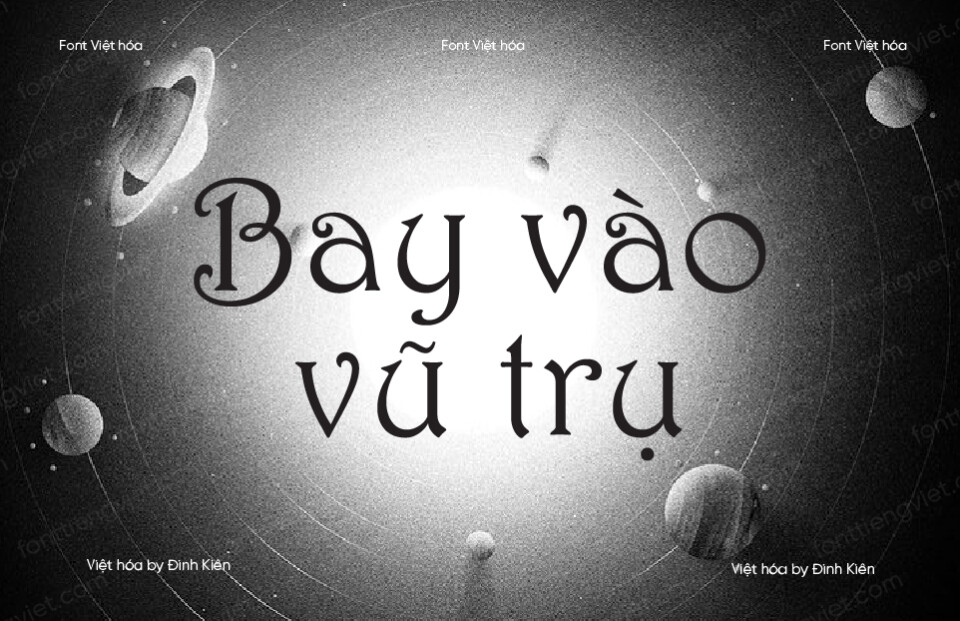
Giới thiệu về Font Việt hóa UTM Harrington
Trong thế giới đồ họa đa dạng, việc lựa chọn một Font Chữ phù hợp đóng vai trò quan trọng để truyền tải thông điệp thẩm mỹ. Font Việt hóa UTM Harrington là một trong những bộ phông chữ nghệ thuật được yêu thích nhất hiện nay. Với những đường nét uốn lượn mềm mại và phong cách quý tộc đặc trưng, bộ font này mang đến vẻ đẹp cổ điển nhưng không kém phần sang trọng. Việc sử dụng Font Việt hóa UTM Harrington giúp các bạn học sinh và giáo viên dễ dàng tạo ra những sản phẩm học tập ấn tượng, từ bìa báo tường đến các bài thuyết trình sinh động.
Đặc điểm nổi bật của Font Việt hóa UTM Harrington
Phong cách thiết kế độc đáo
Đặc trưng của Font Việt hóa UTM Harrington nằm ở các vòng xoắn trang trí tại các đầu chữ cái. Điều này tạo nên sự khác biệt so với các font chữ thông thường, giúp văn bản trở nên nổi bật và thu hút thị giác. Đây là lựa chọn lý tưởng cho các tiêu đề lớn hoặc các thiệp mời sự kiện tại nhà trường.
Khả năng tương thích tốt
Ứng dụng thực tế
Nhờ vẻ ngoài thanh lịch, Font Việt hóa UTM Harrington thường được ứng dụng trong thiết kế logo, bìa sách, menu và các ấn phẩm trang trí nghệ thuật. Trong môi trường sư phạm, font chữ này giúp các em học sinh phát huy tính sáng tạo khi làm đồ án môn học.
Kết luận về Font Việt hóa UTM Harrington